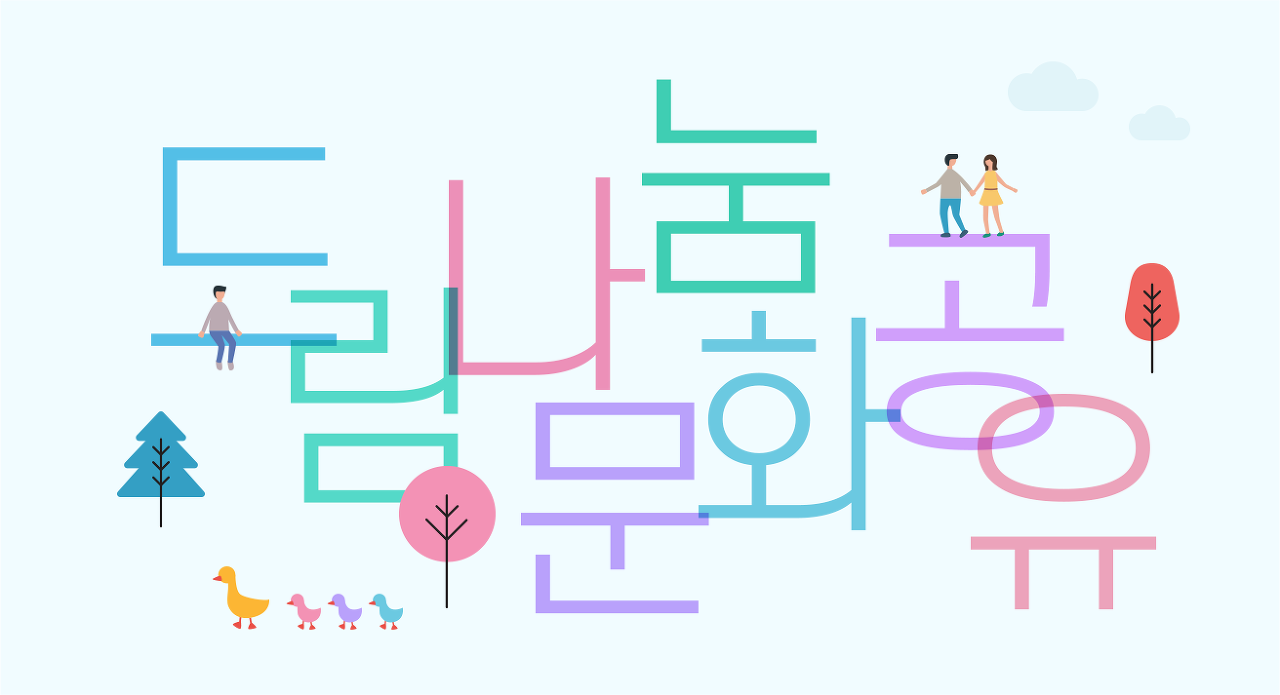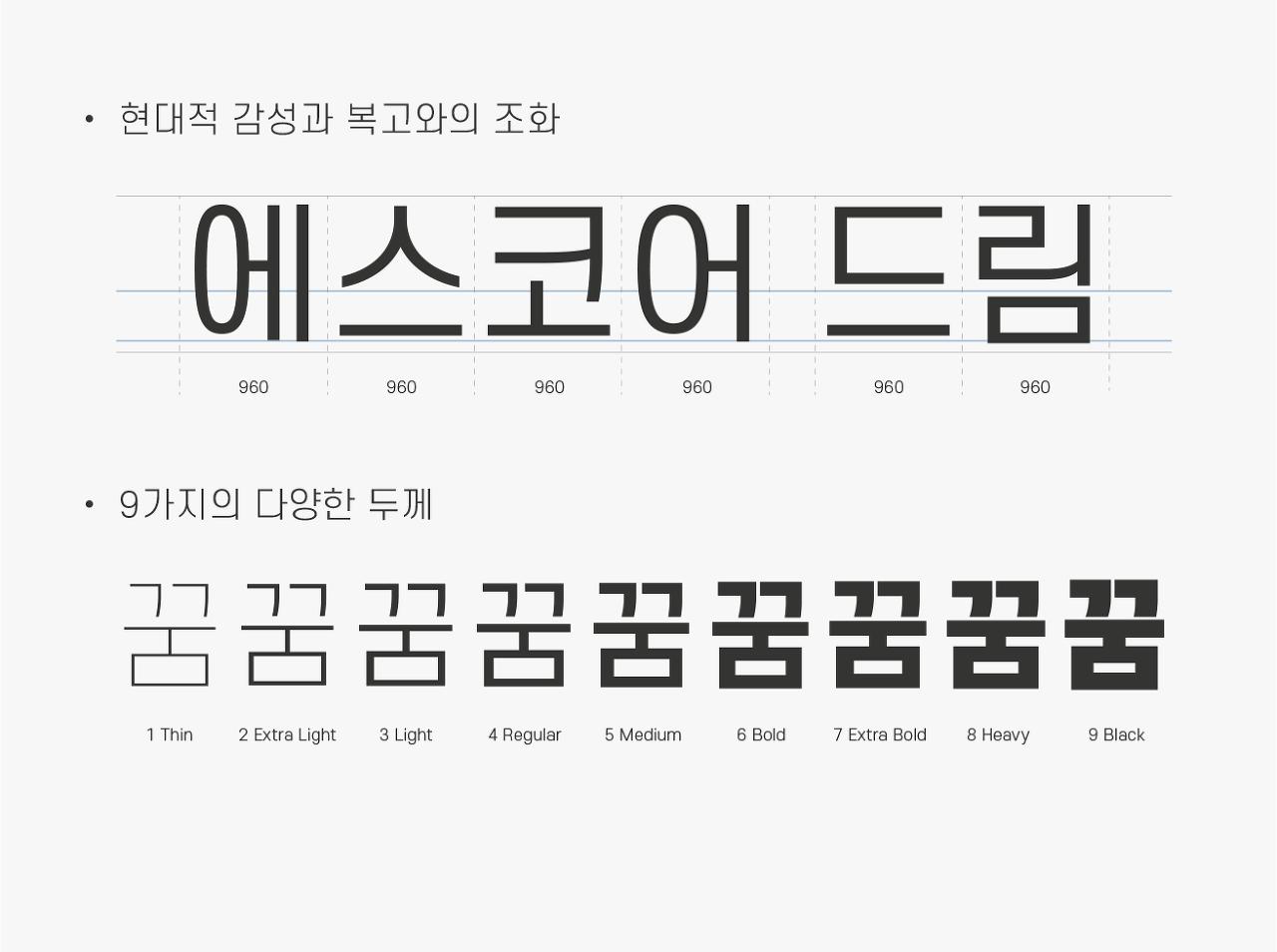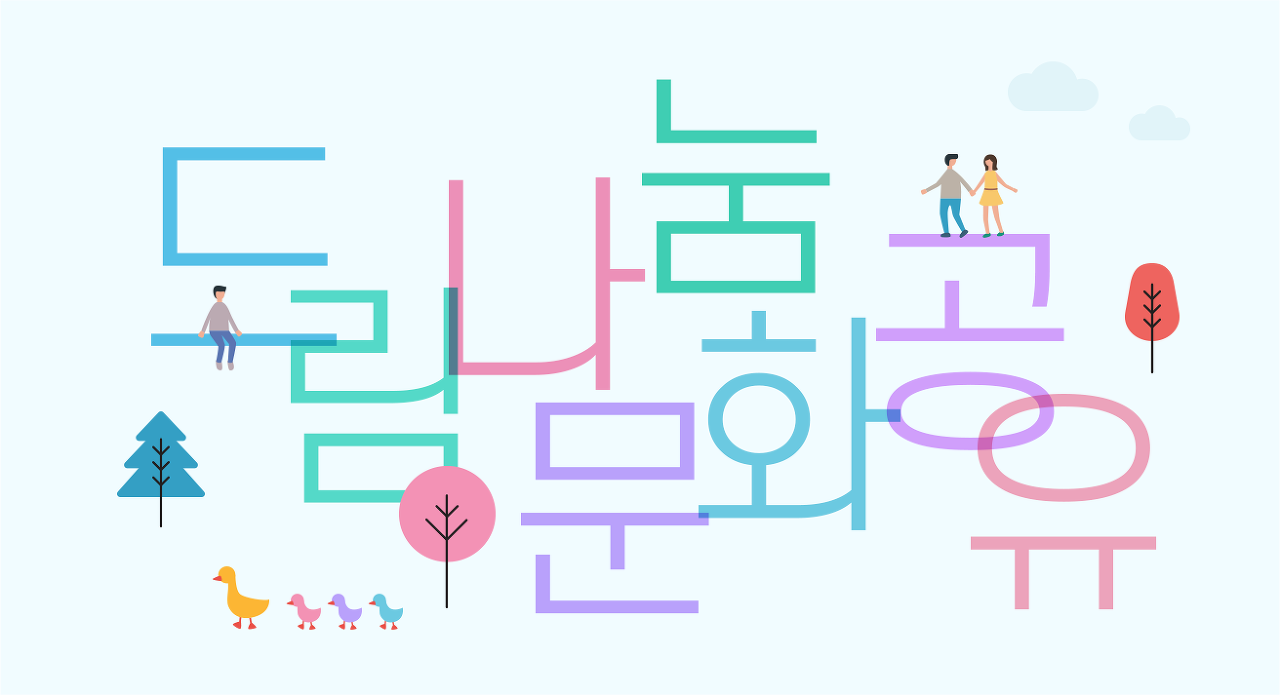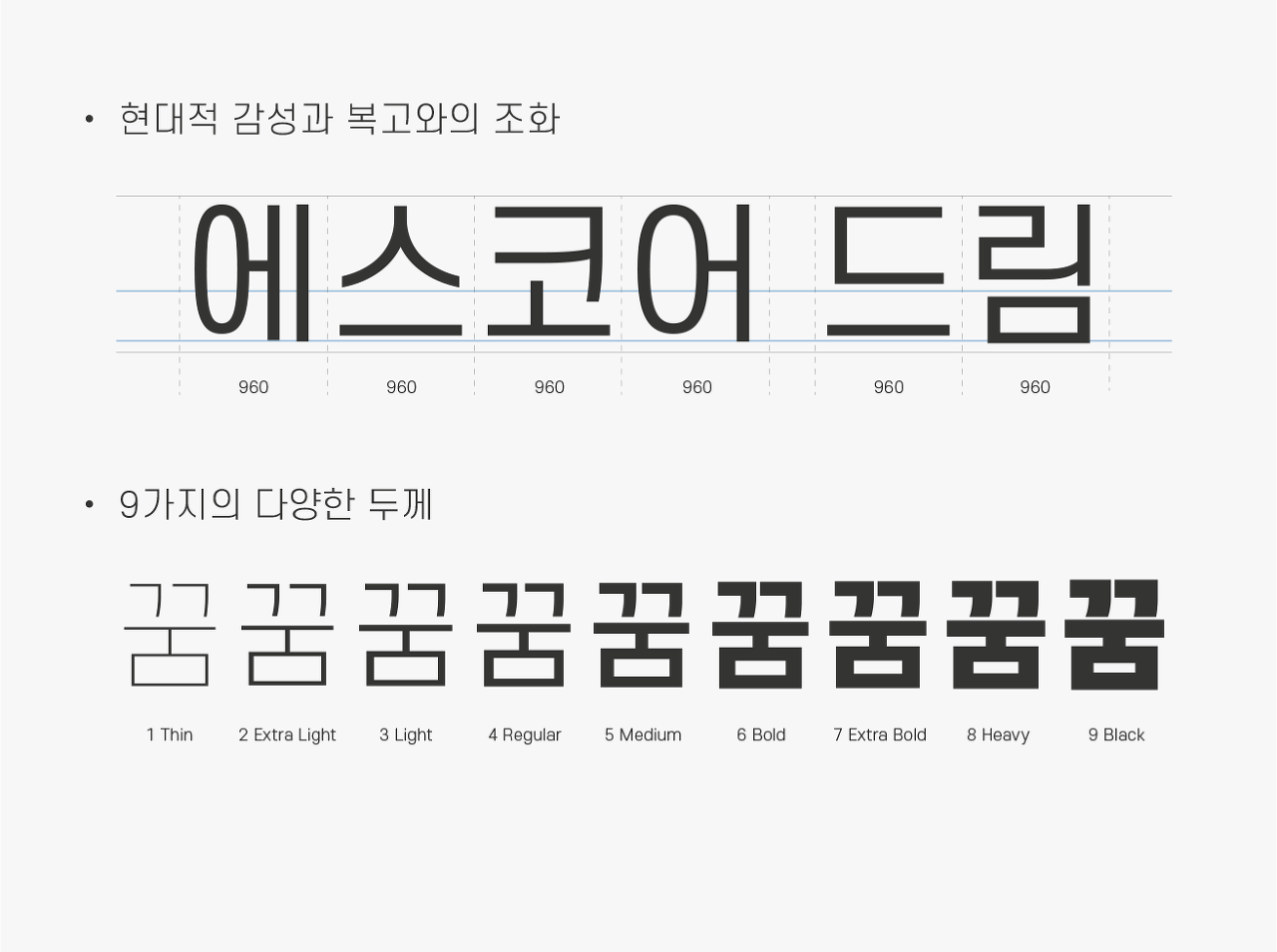
에스코어 드림 (S-Core Dream)
에스코어 드림은 ‘Dream(꿈)’과 ‘드리다’라는 두 가지 뜻을 가지고 있습니다. 꽉 찬 직사각형 구조의 제목용 글꼴로써 복고적인 형태에 현대적인 감성을 담았습니다. 각 자소에서 보여지는 수직적인 획의 마감은 전체적인 구조와 어우러져 새로운 글꼴의 표정을 제시합니다.